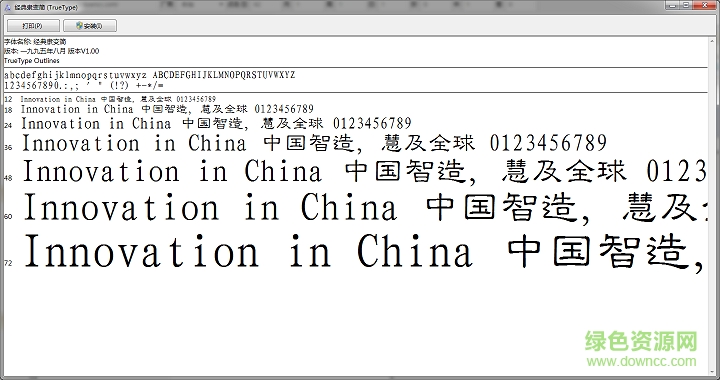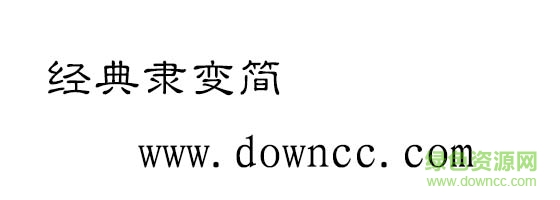
1.中國的字體設(shè)計是在印刷術(shù)的產(chǎn)生和發(fā)展中應(yīng)運而生的。在古代,中國的字體設(shè)計曾有過輝煌的歷史時期,在宋朝時進(jìn)入黃金時代。
2.清朝末年,鉛字排版印刷術(shù)傳入中國,字體設(shè)計進(jìn)入鉛字時代。這個時期的字體設(shè)計既要帶有傳統(tǒng)文化的審美慣性,又要符合鉛字印刷的工藝要求,字體設(shè)計走到了轉(zhuǎn)折的關(guān)口。
3.鉛字印刷是印刷走入機(jī)械化、工業(yè)化時代的標(biāo)志,但在這一時代里,印刷字體設(shè)計卻始終無法超越手工勞動的制約,無法擺脫刻模、鑄字、撿字、排版等一系列印前繁雜工藝的束縛